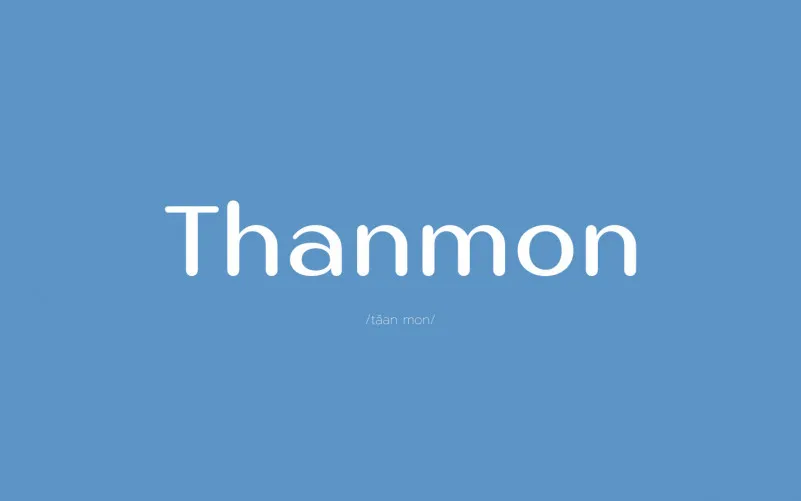
Thanmon Sans Serif Font – Fonte Grátis
Thanmon Sans Serif Font
Descubra Thanmon Sans Serif Font, uma opção fresca e moderna para qualquer projeto visual que você esteja trabalhando. Este tipo de font é perfeito tanto para criações digitais quanto impressas, oferecendo um toque clean e elegante a seus designs. Anupap Jai Chumnan é o criador dessa bela grife de fontes. Free for personal use, Thanmon Sans Serif Font é uma escolha ideal para designers que buscam uma fonte moderna sem comprometer em qualidade. Se você quer incorporar uma versão completa e licenciada da font ao seu projeto empresarial ou comercial, existem opções disponíveis. Anupap Jai Chumnan oferece acesso a um conjunto completo de fonts por meio de suas lojas de pagamento online, onde você pode fazer o download e começar a usar na sua própria plataforma. Para mais informações ou para adquirir uma licença completa, fique à vontade para entrar em contato com Anupap Jai Chumnan pelo email  ou até mesmo doar através do PayPal, no link fornecido. Thanmon Sans Serif Font é um presente para os criativos que desejam incorporar estilos modernos e sofisticados a suas criações. Com sua versão livre para uso pessoal, você pode começar a experimentá-la agora, enquanto a versão completa estará disponível para quem deseja expandir ainda mais seus recursos de design.